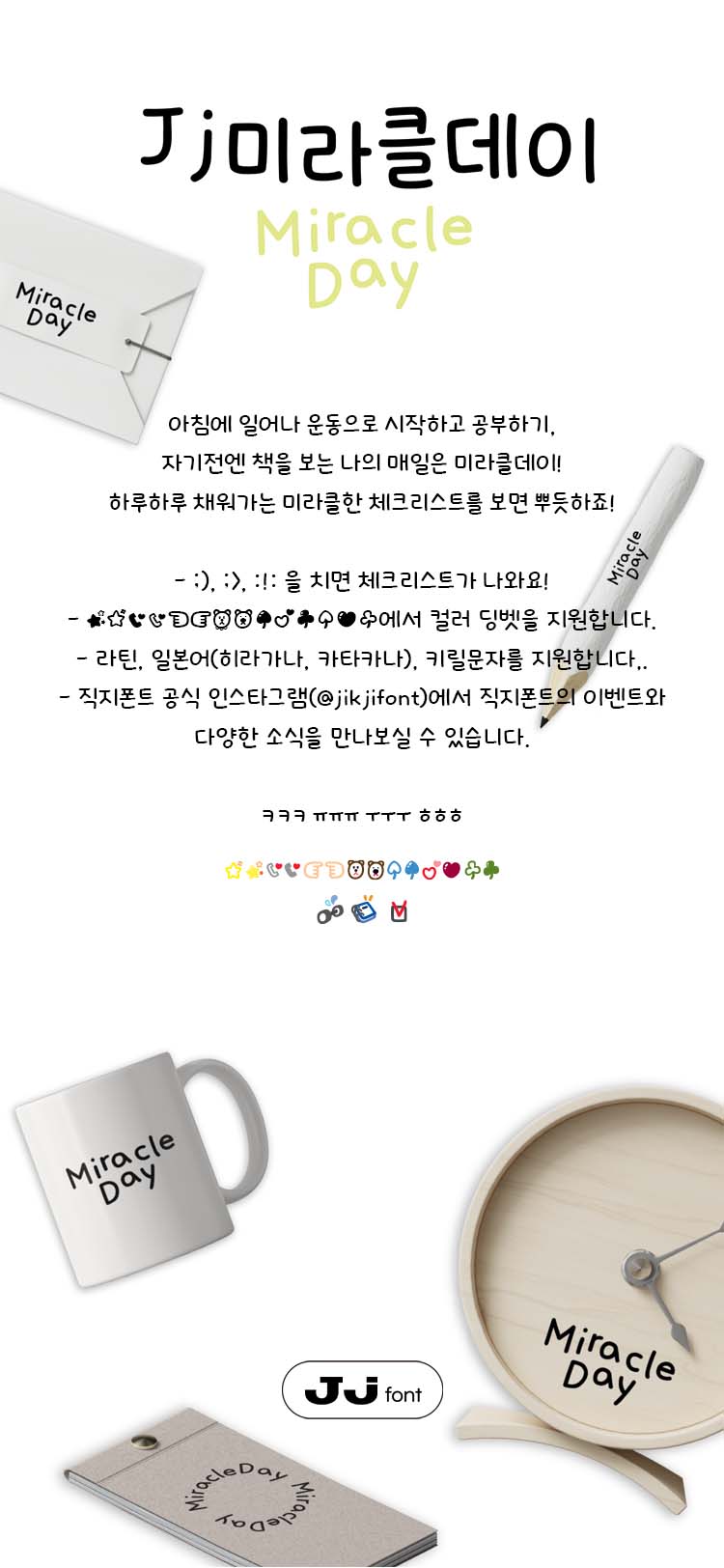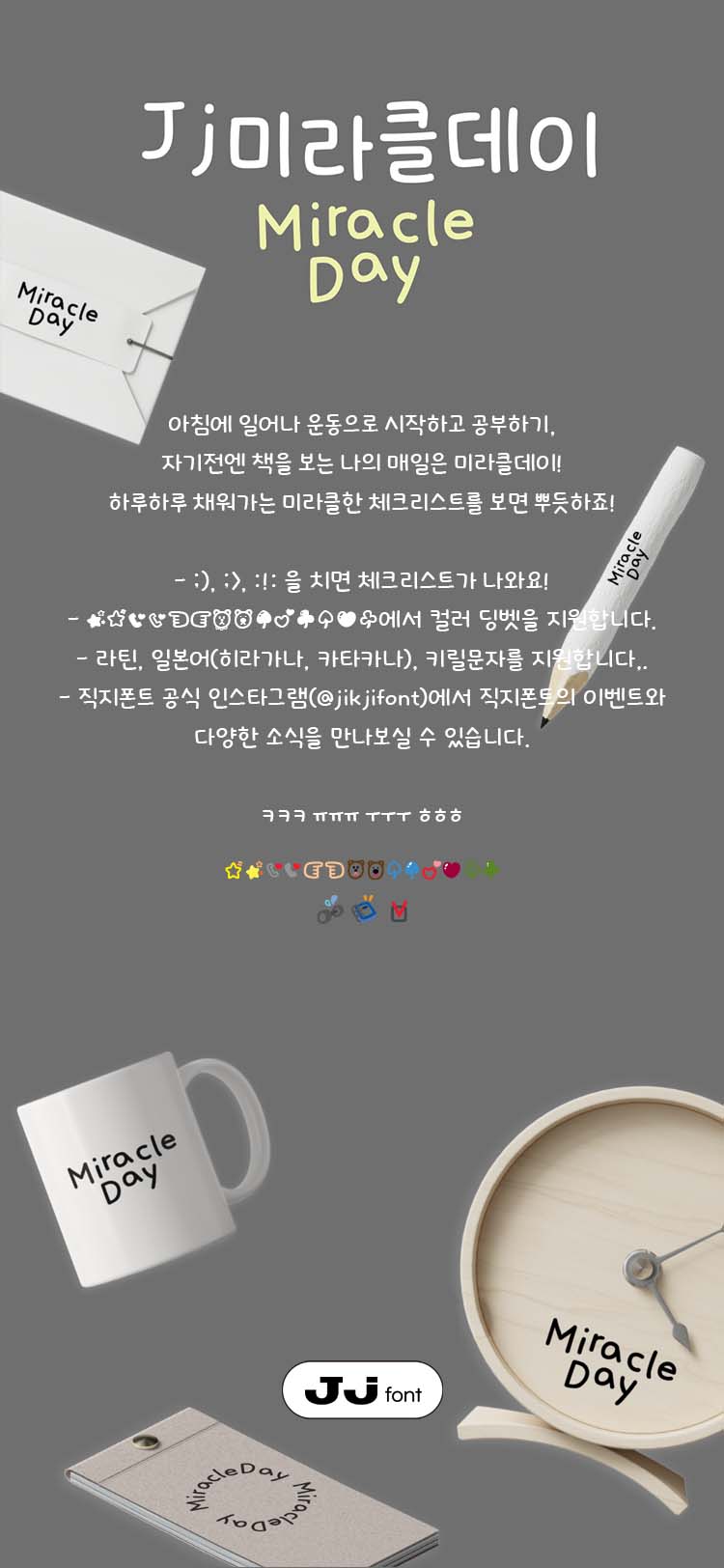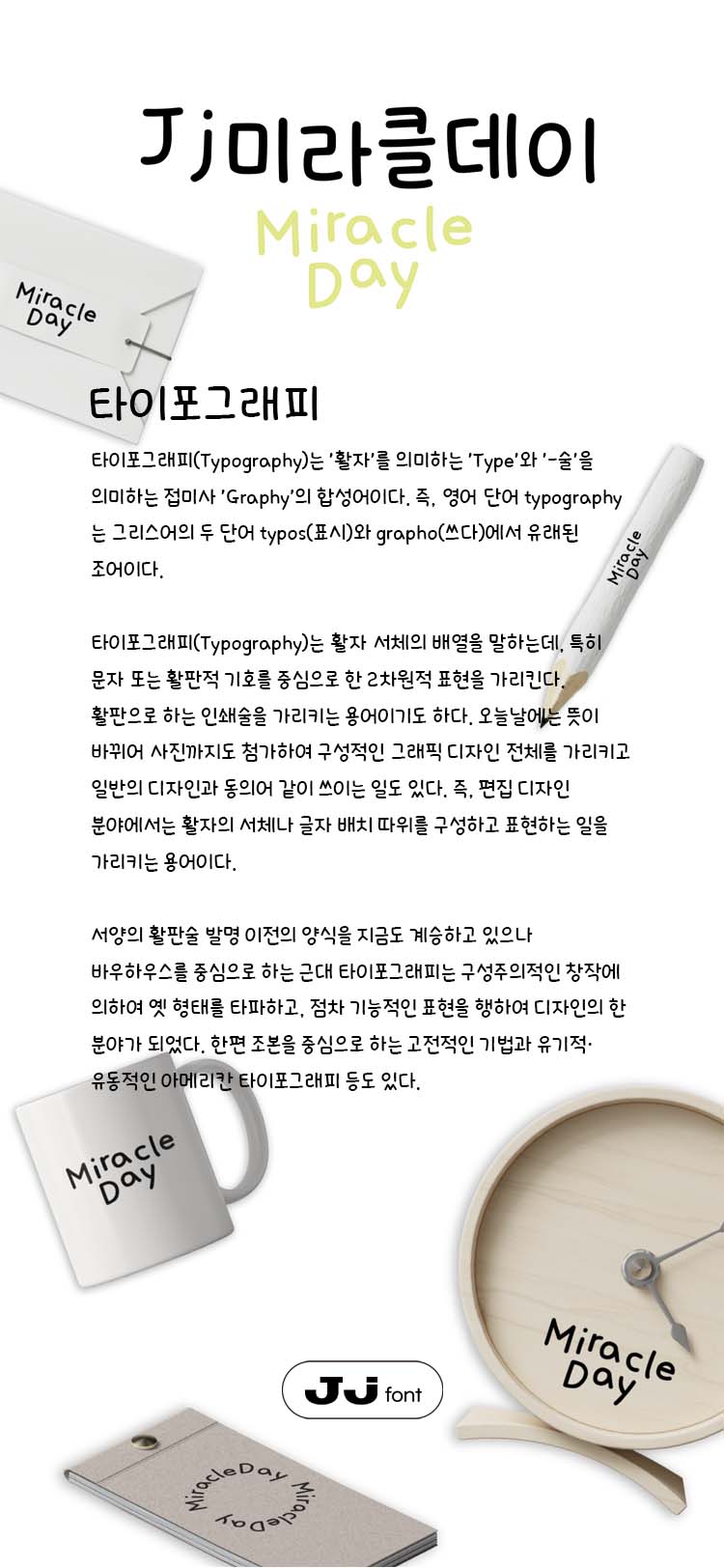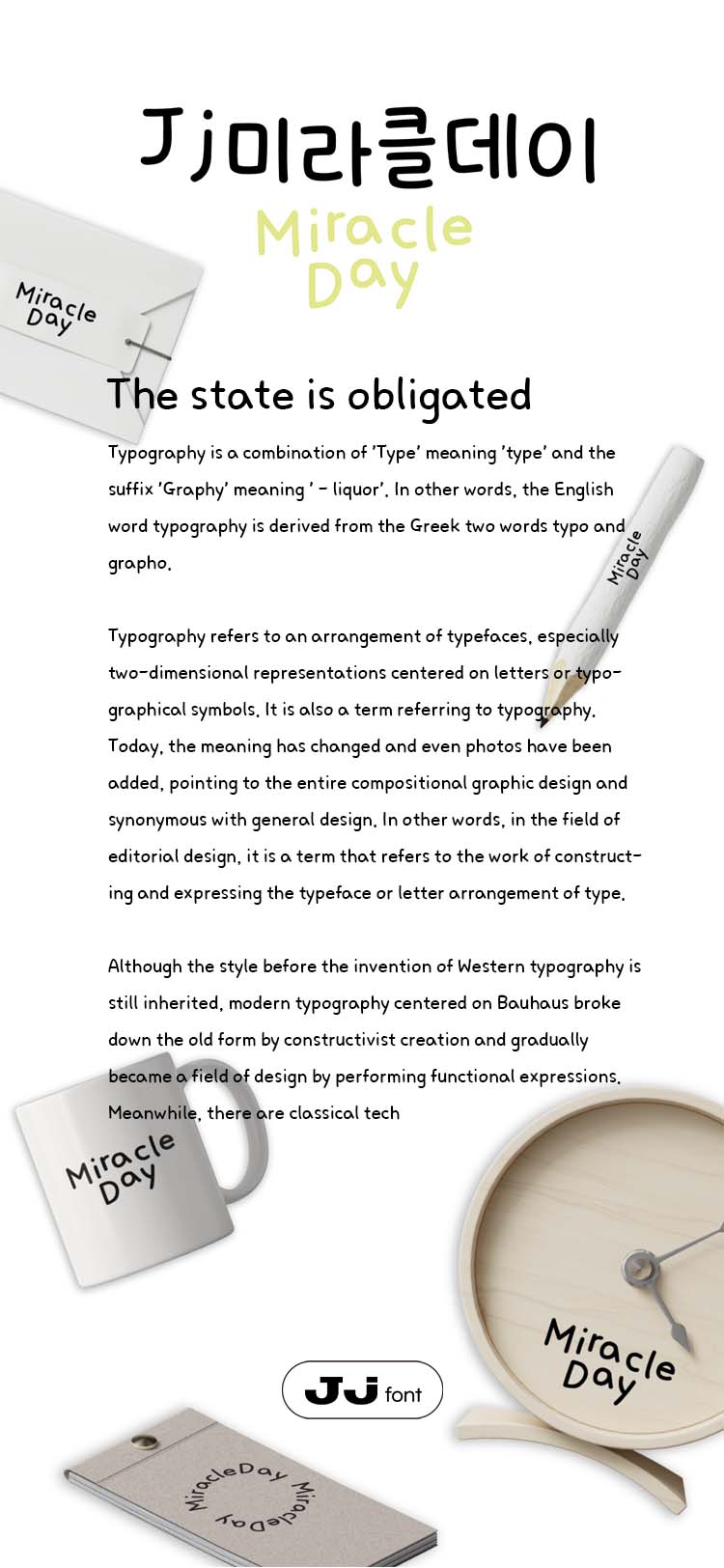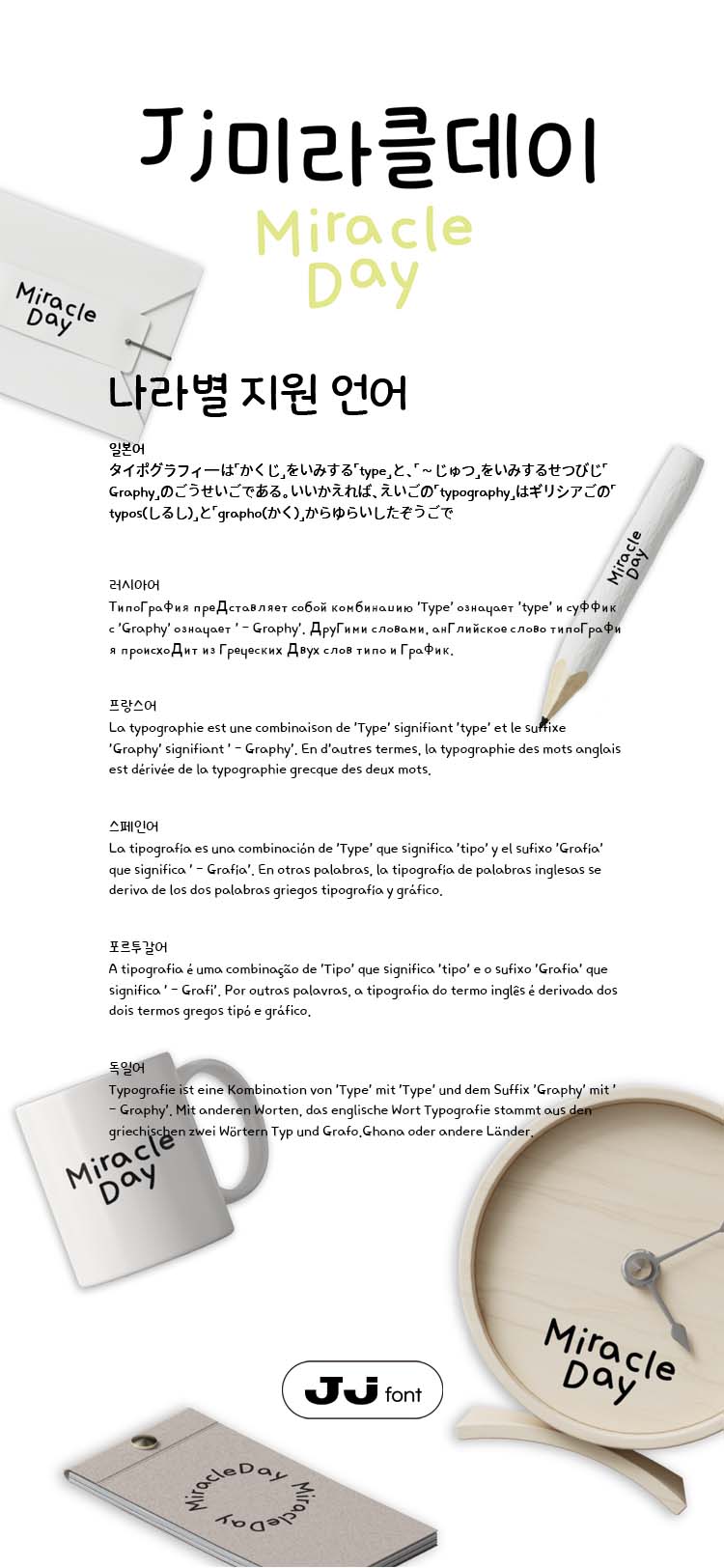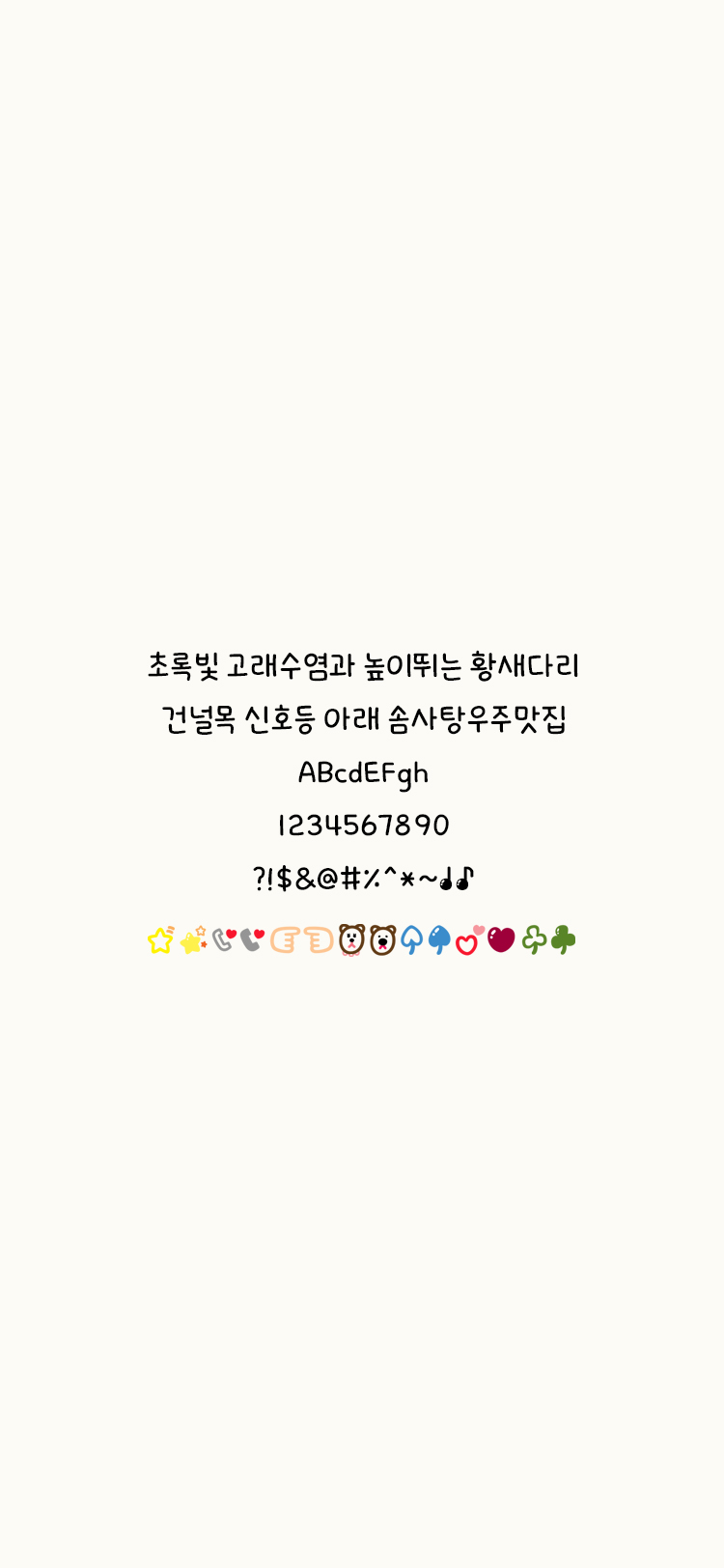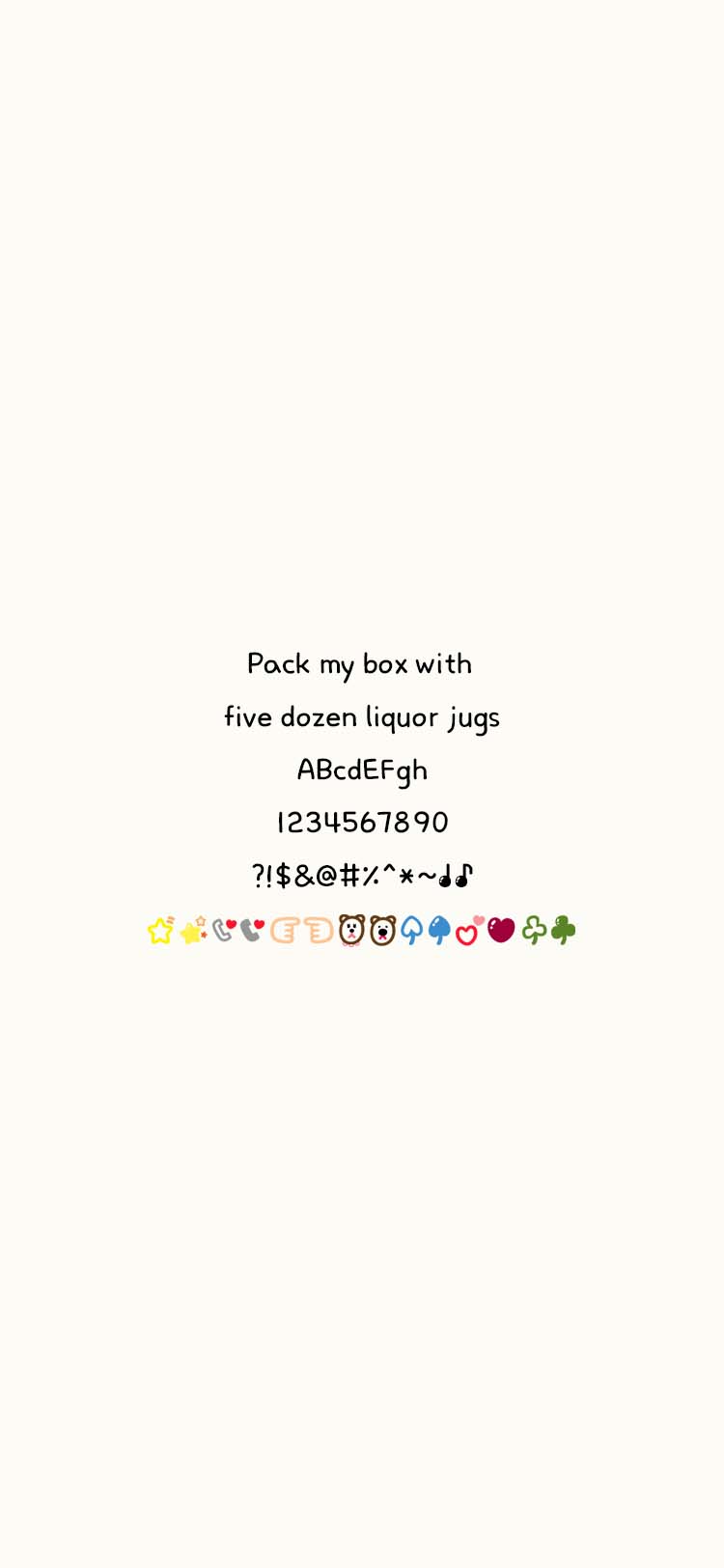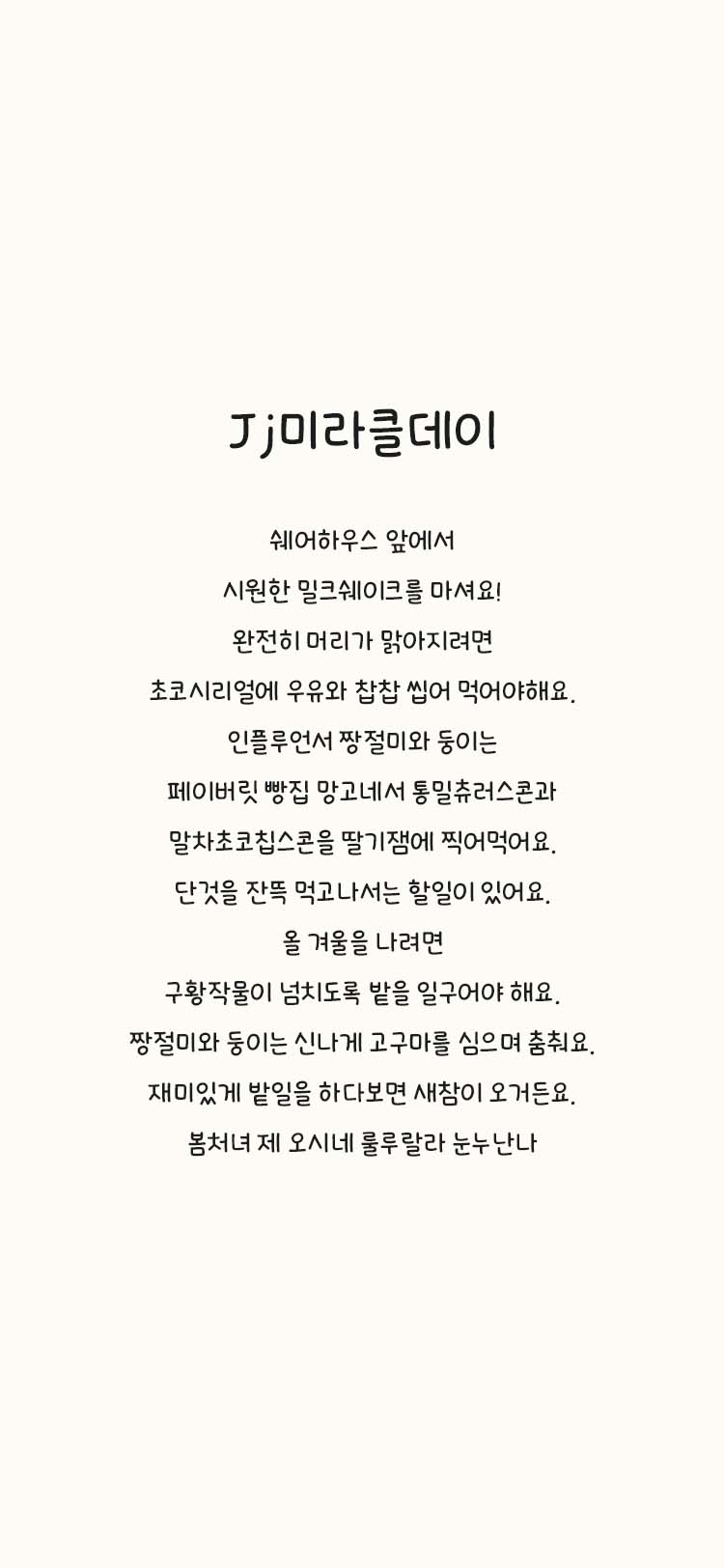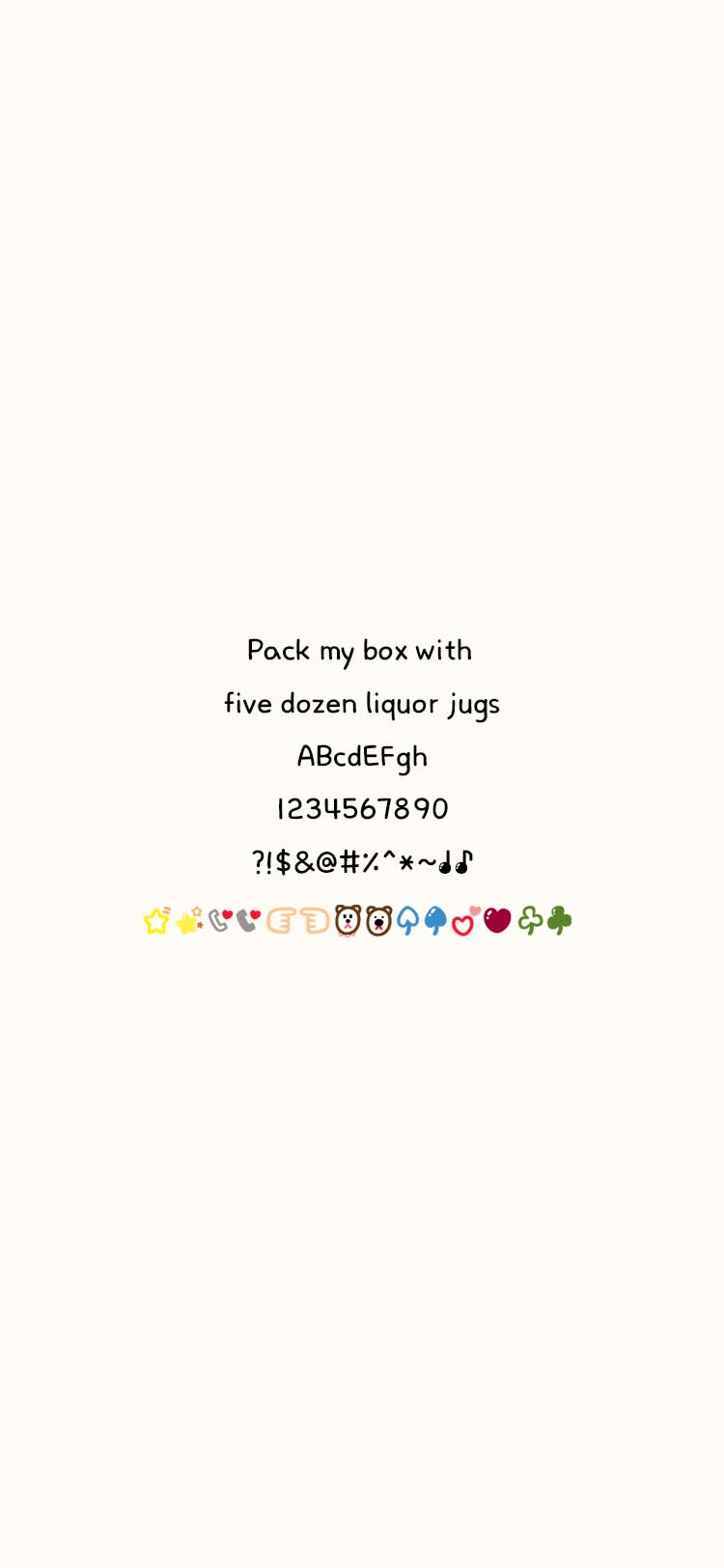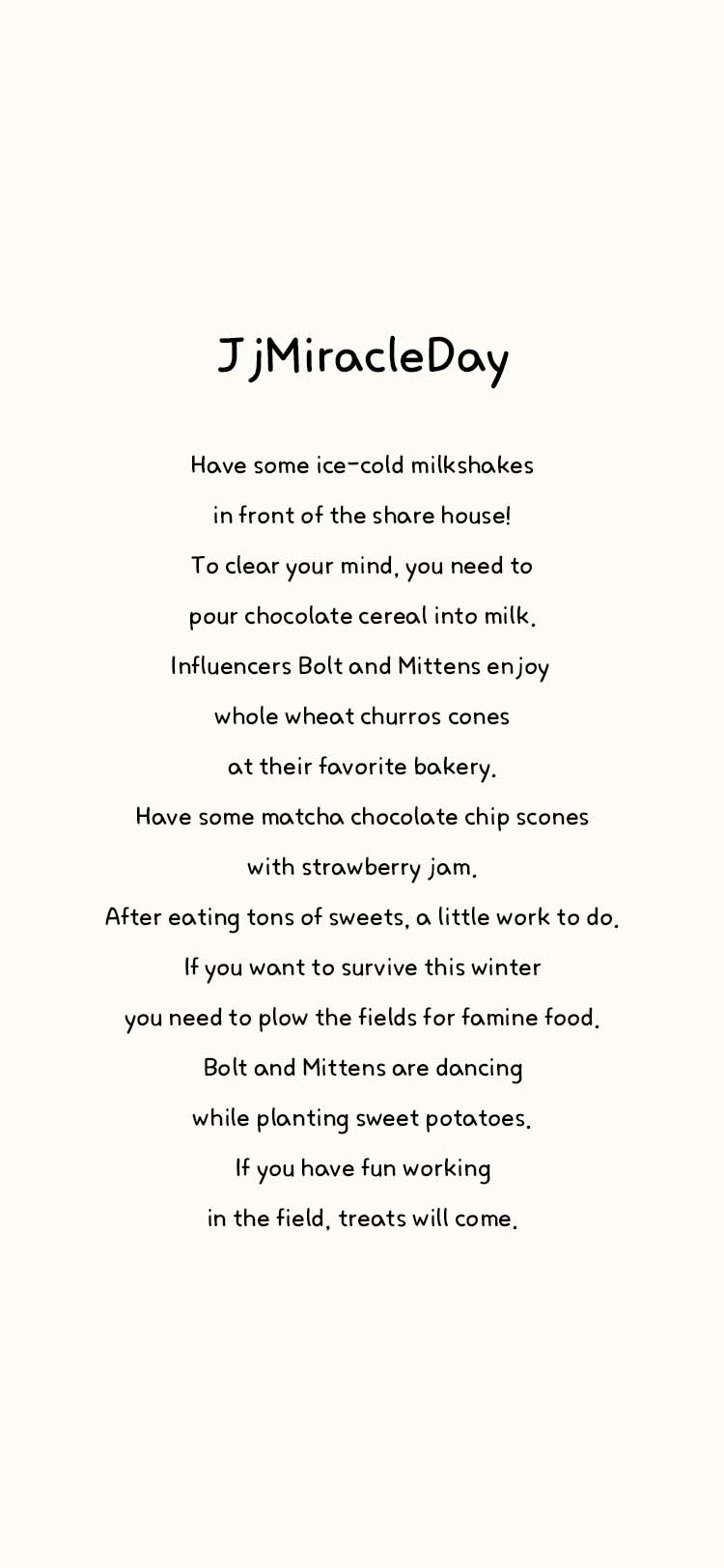
Jj미라클데이
아침에 일어나 운동으로 시작하고 공부하기, 자기전엔 책을 보는 나의 매일은 미라클데이!
하루하루 채워가는 미라클한 체크리스트를 보면 뿌듯하죠!
- ;), ;>, :!: 을 치면 체크리스트가 나와요!
- ♂♀☆★♡♥에서 컬러 딩벳을 지원합니다.
- 라틴, 일본어(히라가나, 카타카나), 키릴문자를 지원합니다,.
• Jj미라클데이 / JjMiracleDay